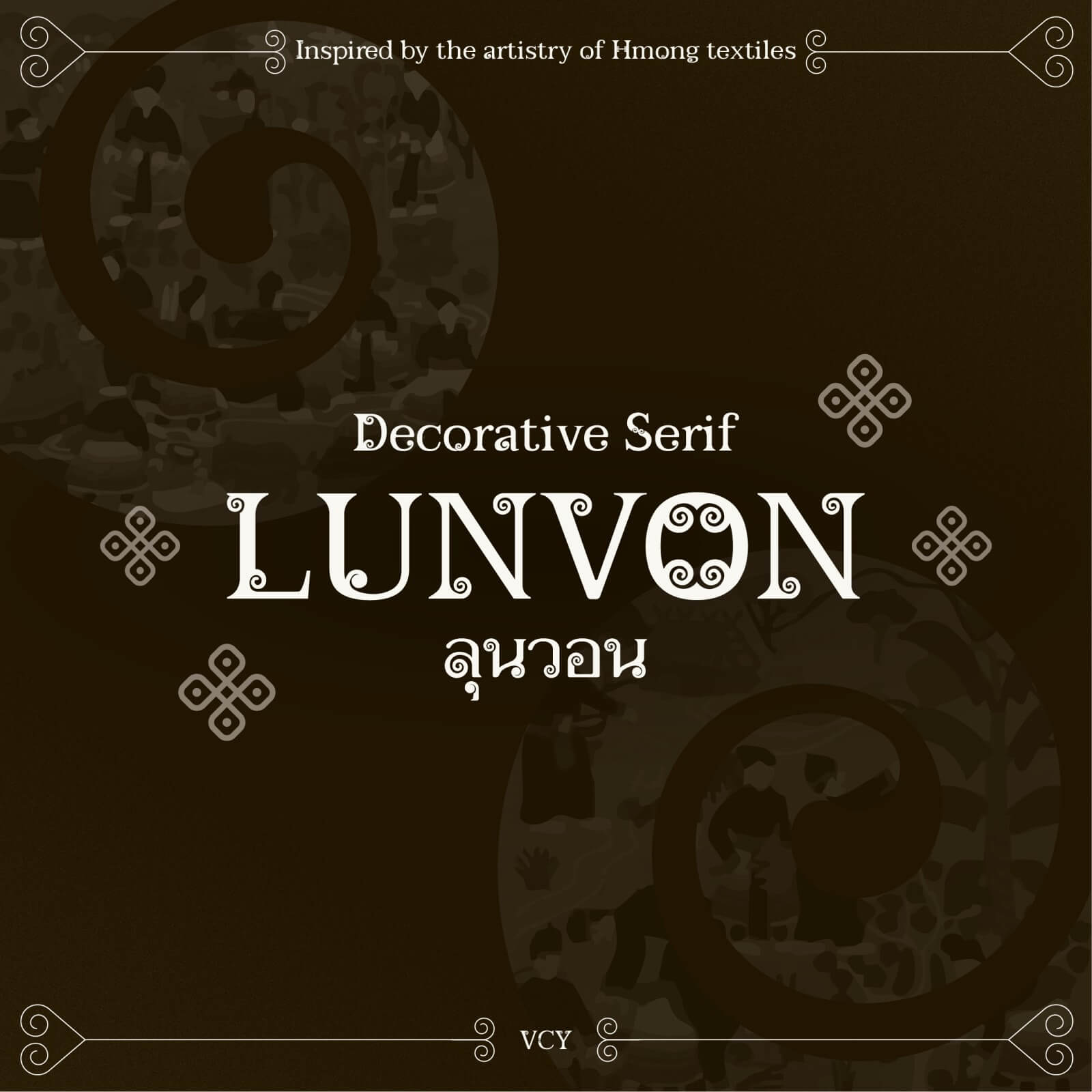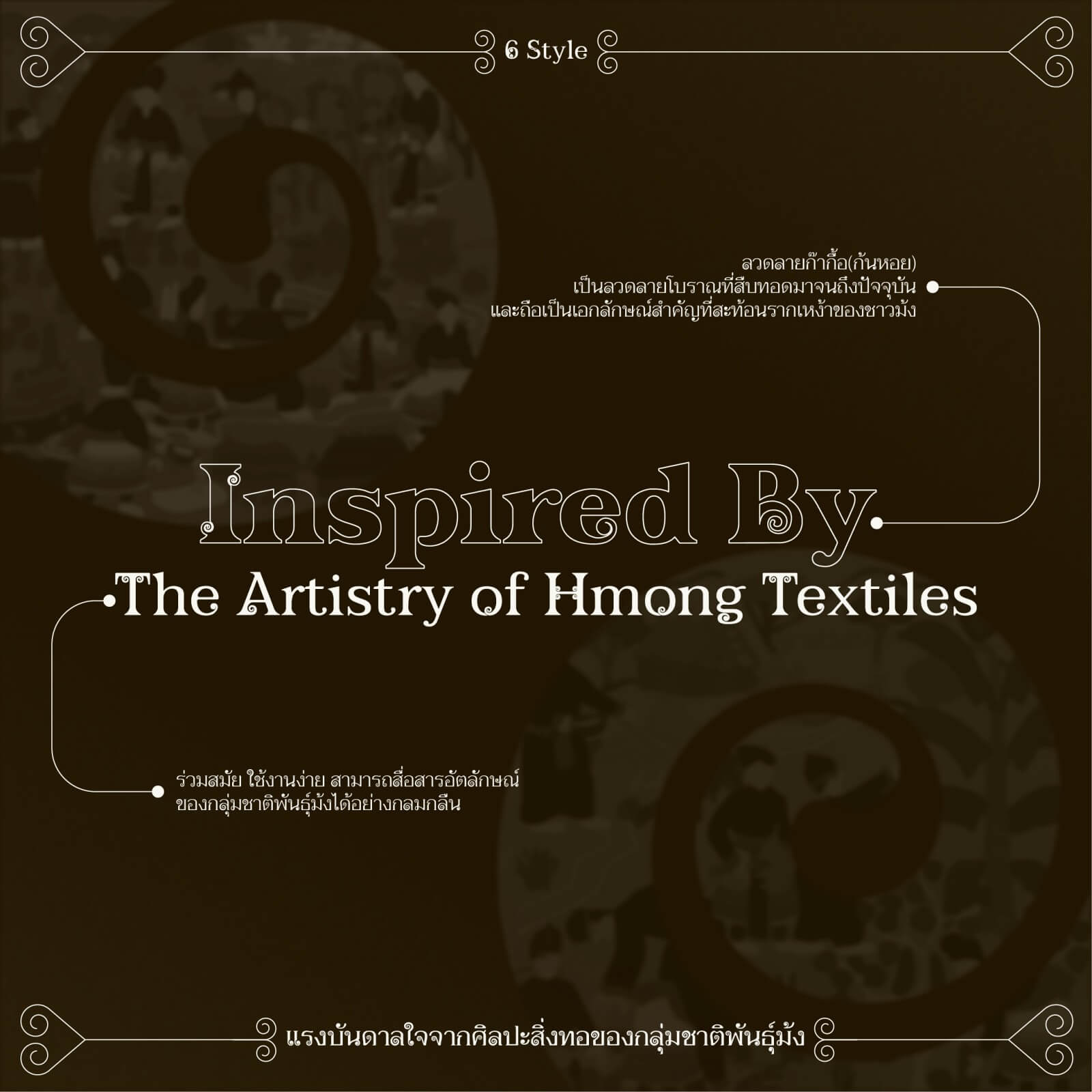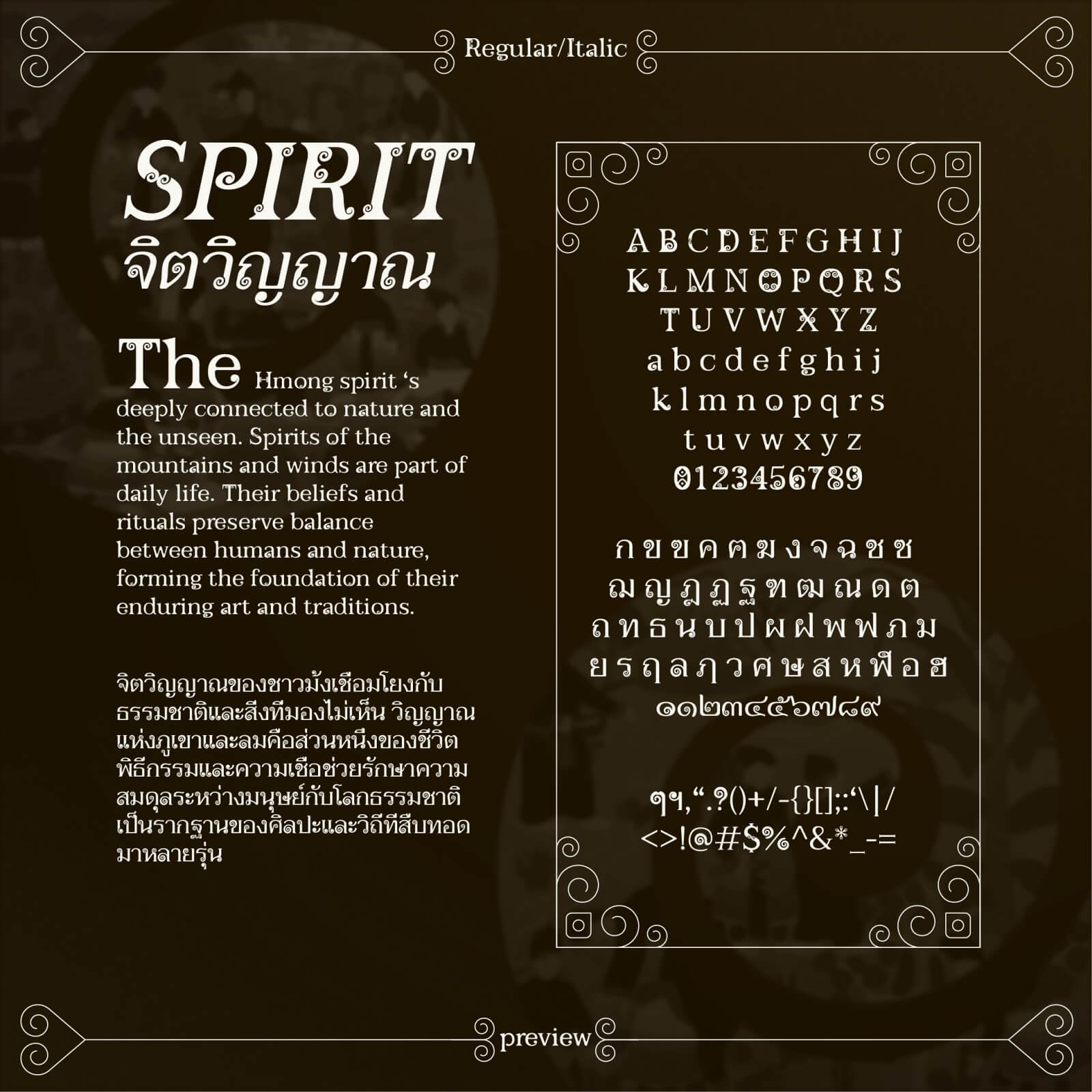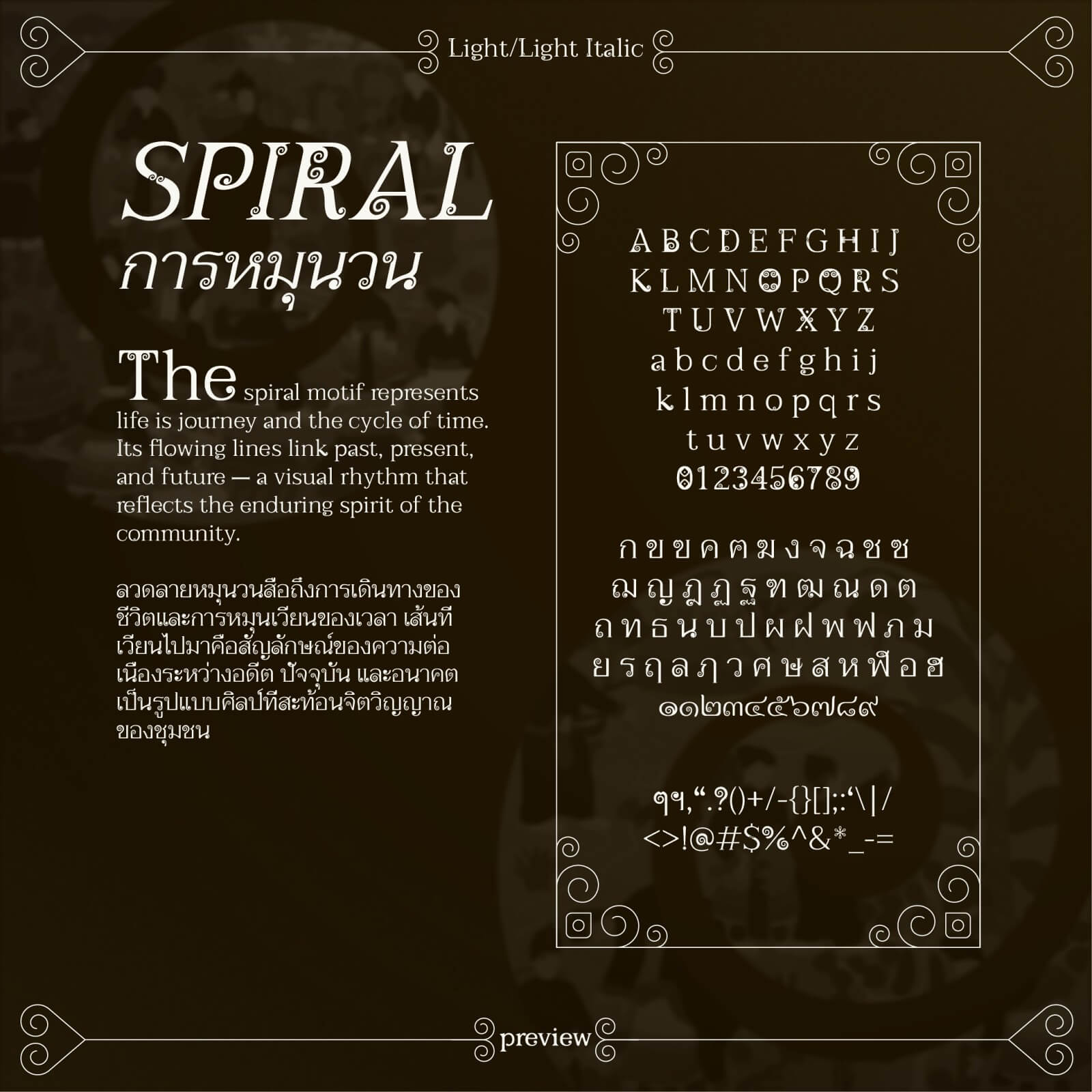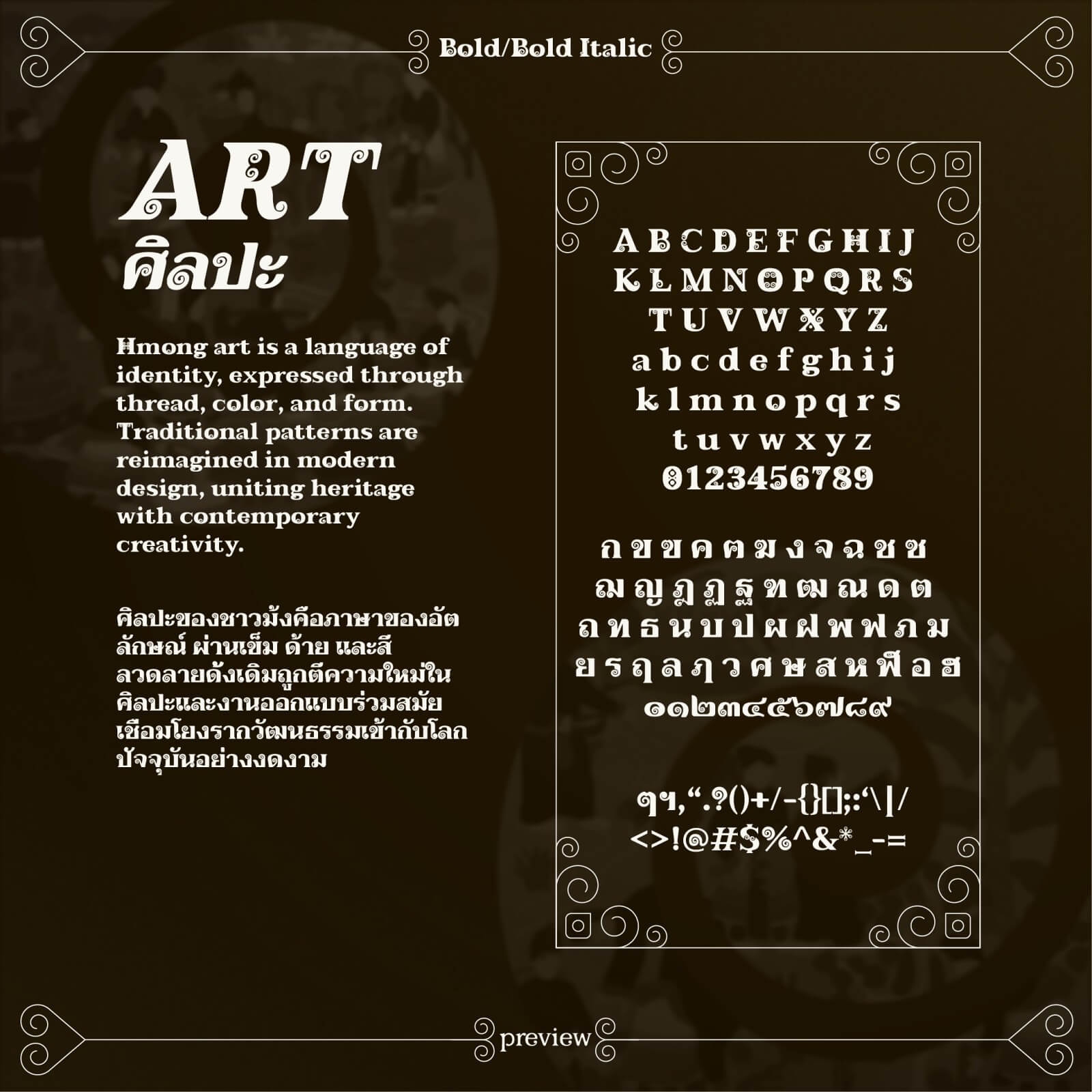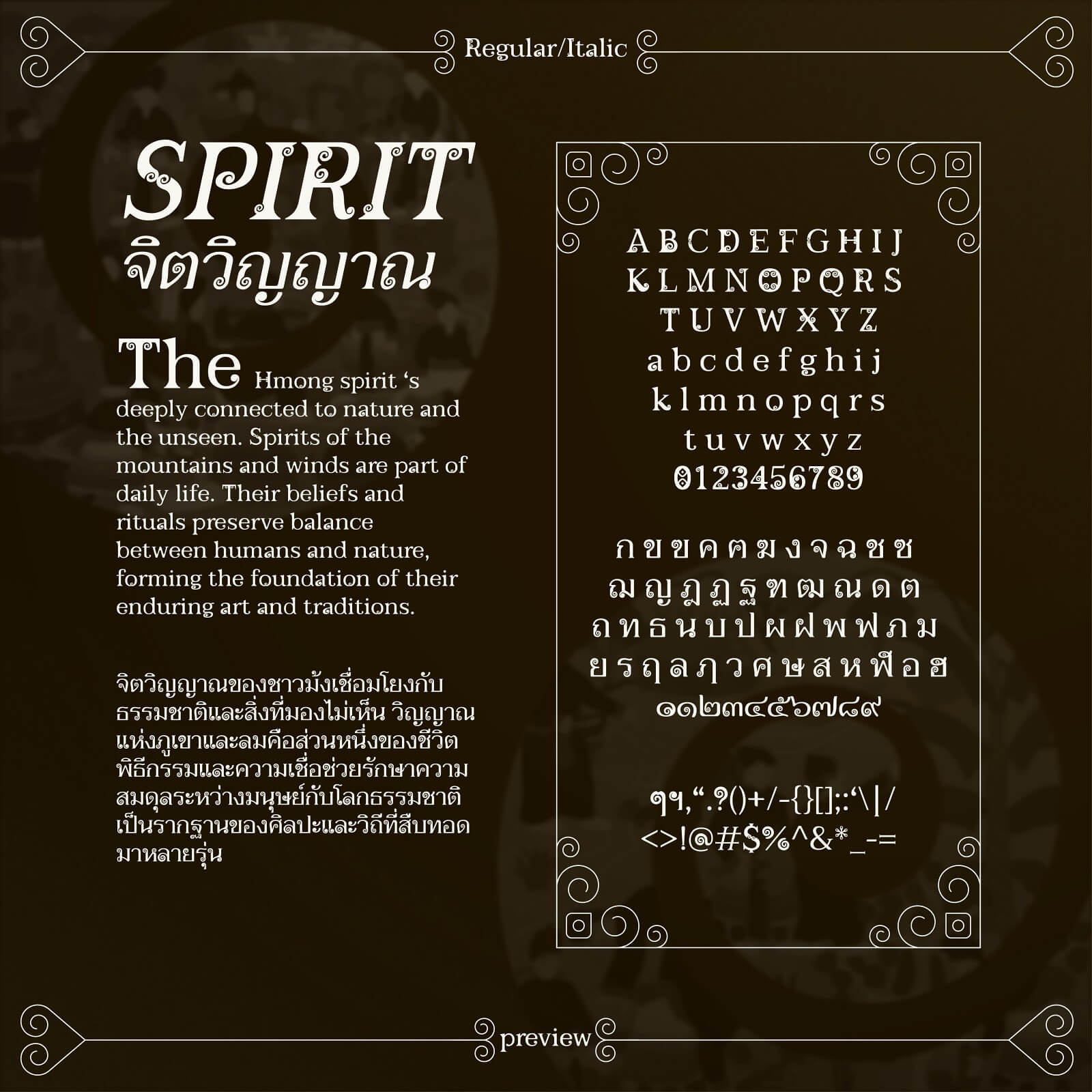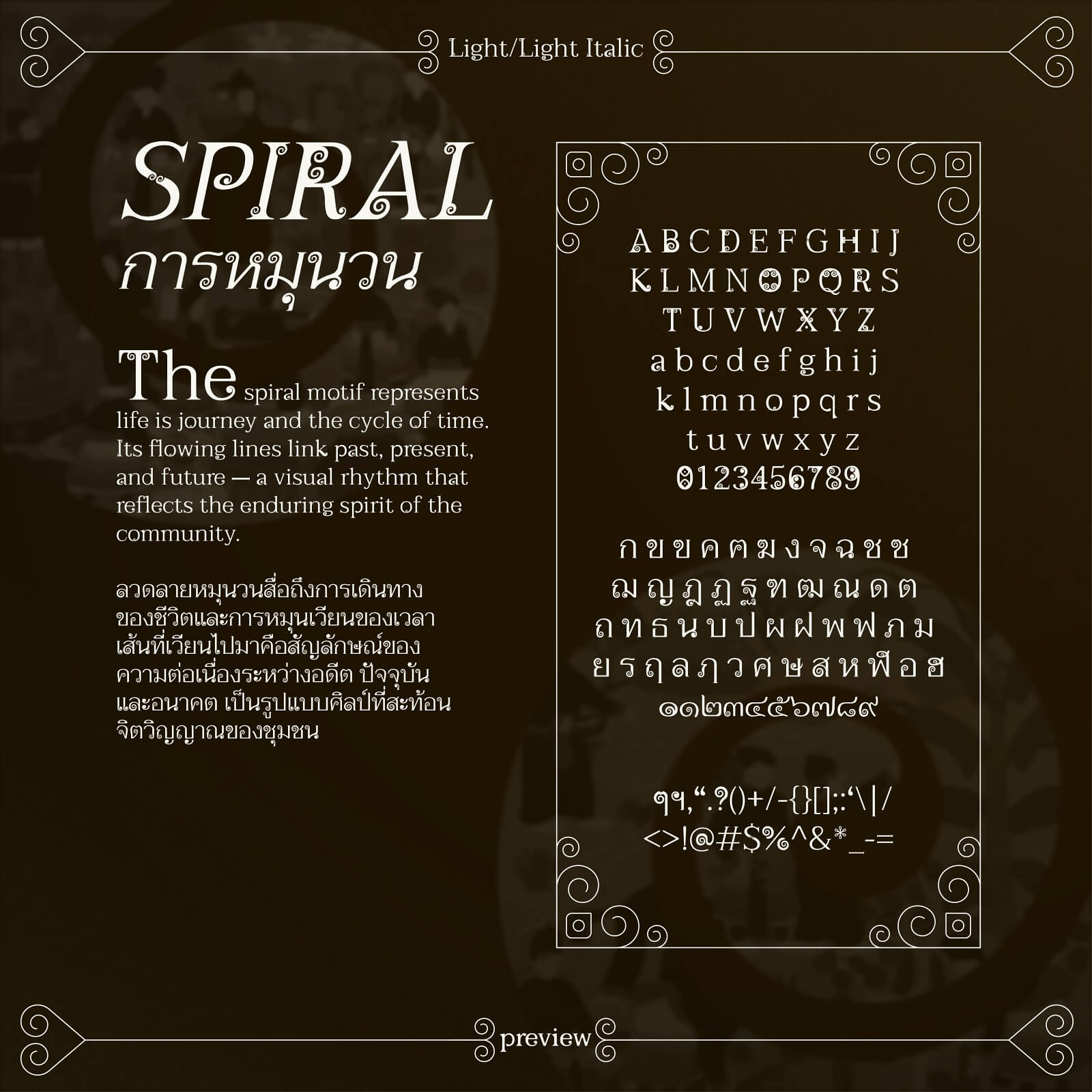
ลุนวอน (Lunvon)
ลุนวอน – เป็นฟอนต์ที่ได้รับแรงบันดาลใจจากลวดลายผ้าของกลุ่มชาติพันธุ์ม้งในภาคเหนือ ลวดลายที่ใช้ในการออกแบบเป็นหลักคือลายก๊ากื้อ (ก้นหอย) ซึ่งเป็นลวดลายโบราณที่สืบทอดมาจนถึงปัจจุบัน และถือเป็นเอกลักษณ์สำคัญที่สะท้อนรากเหง้าของชาวม้ง
และผสมผสานลวดลายอื่น ๆ เช่น ลายหูเสือ ลายก้นหอยมีหาง ลายตาปลา และลายผักกูด ในบริบทของการออกแบบลวดลายก้นหอยยังสื่อถึงความเคลื่อนไหวและการหมุนเวียนอย่างไม่หยุดนิ่ง ซึ่งสอดรับกับแนวคิดในการออกแบบฟอนต์ที่ว่า “ความงามของศิลปะที่ไม่เคยหยุดนิ่ง แต่ยังคงรักษารากเหง้าในทุกการเปลี่ยนแปลง“
Lunvon Font Family (2025)
Font Name : Lunvon
Designer : VCY
Based on : Taviraj (2015) by Cadson Demak